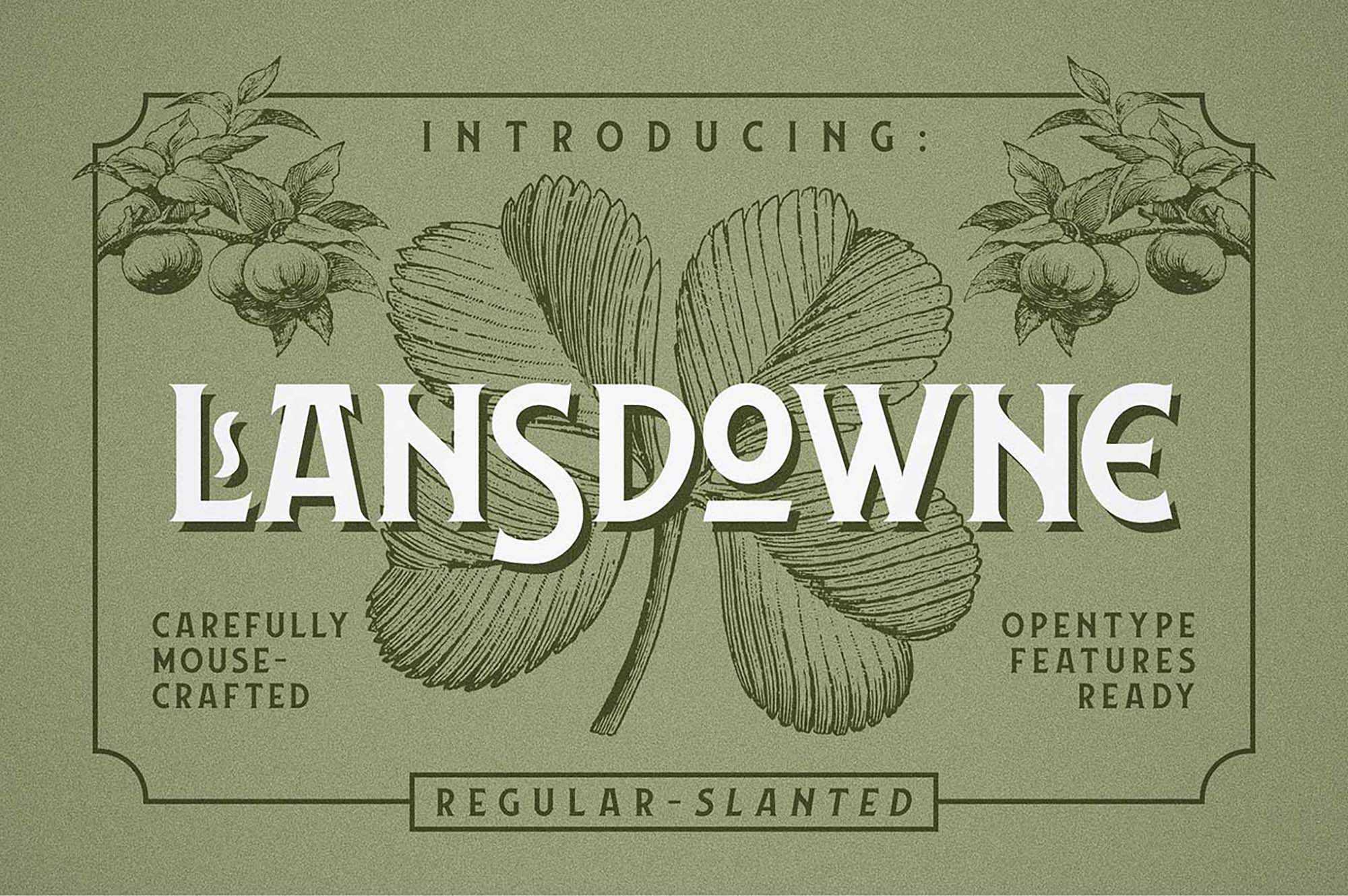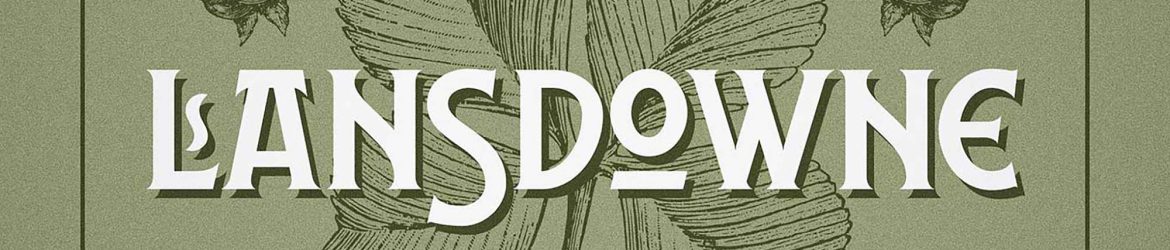
Lansdowne Decorative Font – Download Grátis
Lansdowne é um fonte decorativa criado pela Twicolabs Fontdation, trazendo uma mistura única de letras vintage e caracteres extravagantes em duas formatos, OTF e TTF. Se você está procurando por um recurso gráfico que ofereça tanto uma viagem nostálgica quanto algo inusitado e criativo, Lansdowne é a escolha certa. Esta fonte é perfeita para projetos impressos variados, incluindo cartões de negócio, flyers, convites, desenhos de roupas, capas de livros e até mesmo para design de sites, marca, logotipos e outros tipos de design digital. Sua natureza única e atraente, tanto no formato vintage quanto no seu caráter extravagante, o torna ideal para qualquer projeto que busque um toque diferenciado. Que tal adicionar esse charme à sua próxima criação gráfica?